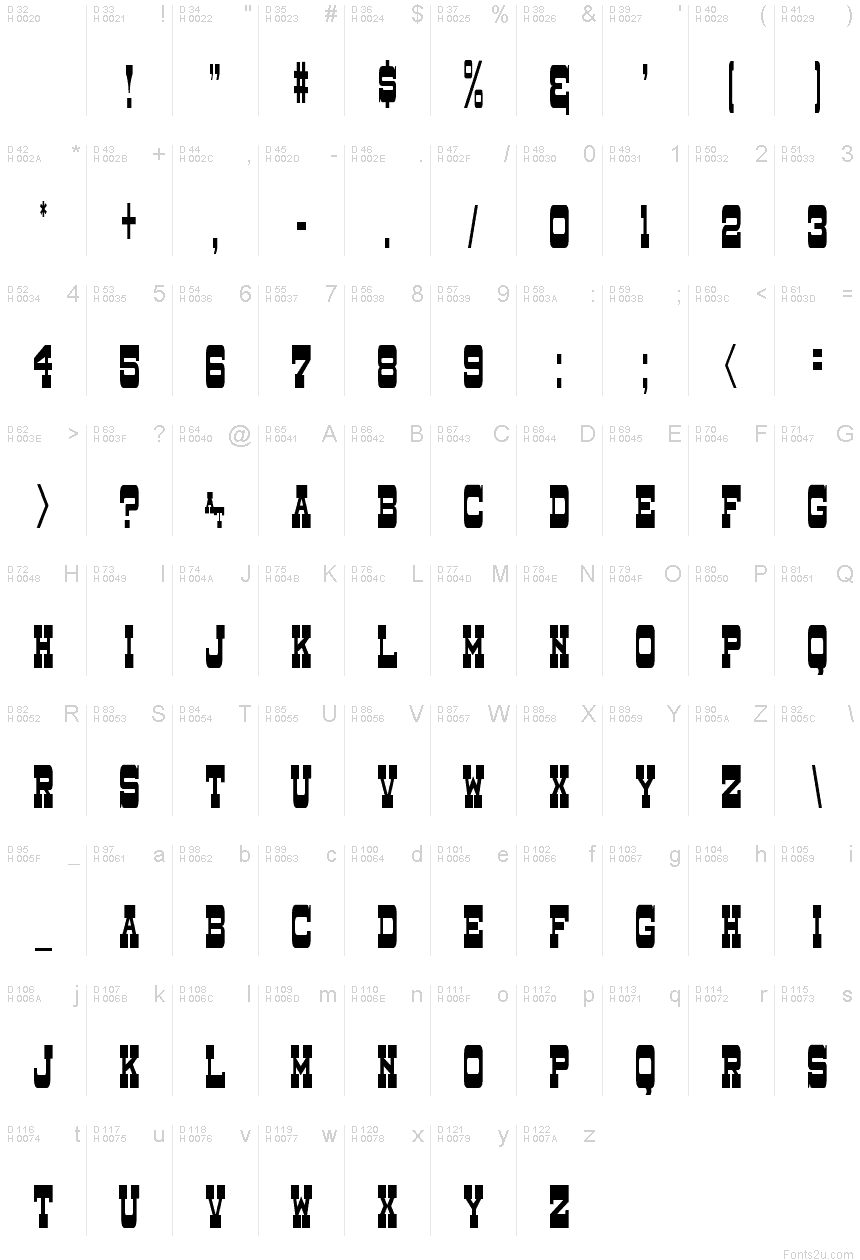
Dry Goods Narrow JL de Jeffrey N. Levine es una tipografía display gratuita de estilo western que condensa el dramatismo de los viejos letreros de madera en una silueta esbelta y vertical. Sus letras altas y cuadradas parecen grabadas en madera ruda: trazos gruesos, espacios internos ajustados y esas muescas distintivas que evocan al instante el espíritu de la frontera. Al ser condensada pero contundente, logra ese impacto visual tipo saloon incluso donde el espacio es escaso, desde etiquetas de botellas hasta titulares en carteles.
Al usar Dry Goods Narrow JL, tus diseños pueden invocar la esencia de los folletos de rodeo, la señalética de tiendas de época o la identidad visual de un bar rústico sin parecer cursi. Esta tipografía gratuita destaca en carteles de eventos, menús de barbacoa, packaging temático, miniaturas de YouTube, merchandising y logotipos que buscan fuerza y teatralidad. Combínala con una fuente sans serif sencilla y limpia en los textos más pequeños para que la energía del viejo oeste se concentre en los titulares.